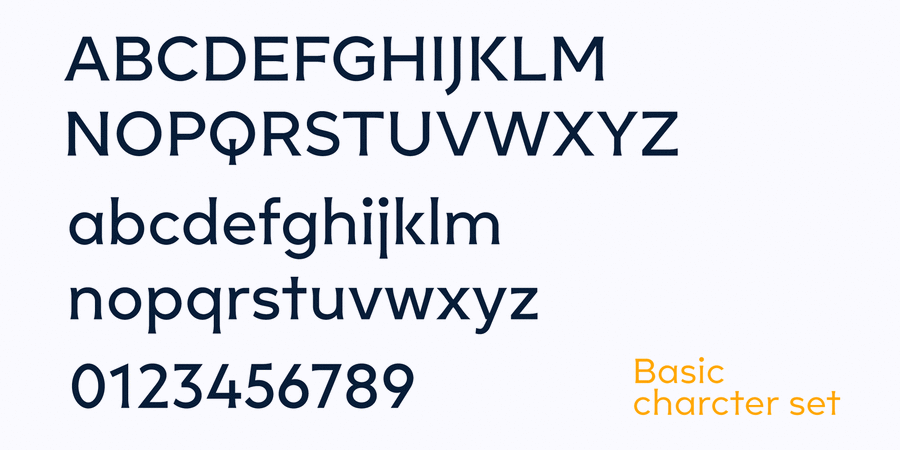
Zerno (18 шрифтів)
Zerno – гліптальний шрифт із геометричним корінням. Його симетричні делікатні засічки нагадують техніку різьблення по каменю. Завдяки насиченості від тонкого до наджирного, гарнітура досить універсальна, щоб її можна було використовувати в будь-якому середовищі – від екрану до рубленого граніту, від плакатів до акцентованого тексту. Шрифт розробив Олег Ліщук у 2021 році.
Особливості сімейства шрифтів ZernoХіт десятиліття:
Асоціації з сімейством шрифтів ZernoОсобистість і характер гарнітури:
тонкий, худий, витончений, холодний, делікатний, легкий, свіжий, модний, якісний, культурний, добірний, благородний, гармонійний, елітний, дорогий, красивий, майстерний, знаменитий, оригінальний, багатий, міський, прозорий, гострий, точний, статичний, чіткий, західний, рівний, розкішний, елегантний, ювелірний, естетичний, дорогоцінний, гламурний, сексуальний, ефектний, виразний, характерний, прекрасний, аристократичний, історичний, пафосний, унікальний, імперський, стійкий, переконливий, серйозний, значний, обов'язковий, солідний, стабільний, добротний, цінний, самостійний, відповідальний, твердий, надійний, яскравий, артистичний, кам'яний, різкий, сильний, героїчний, легендарний, мотивуючий, помітний, фундаментальний, урочистий, епічний, амбітний, авторитетний, римський, владний, видовищний, грандіозний, великий, величний, монументальний, впевнений, архітектурний, кінематографічний, християнський, традиційний, офіційний, важкий, квадратний, блатний, залізний, сталевий, колючий
парфумерія, дієта, туалетна вода, срібло, АСМР, краса, мода, ювелір, музика, ресторан, розкіш, гламур, Інстаграм, люкс, прикраса, дизайн, годинник, бутік, парфуми, преміум, готель, шоколад, коштовності, сервіровка, золото, музей, меморіал, пам'ятник, надгробок, скульптура, історія, меч, карти, мистецтво, архітектура, алкоголь, банкнота, монета, гроші, банк, акція, цінні папери, облігація, тютюн, віскі, фінанси, ломбард, антикваріат, гра, сигари, Барбершоп, Трофей, нагорода, кава, правосуддя, влада, суд, імператор, архітектор, обід, вечеря, кіно, сир, легенда, комп'ютерна гра, Біблія, взуття, бар, юрист, адвокат, нотаріус, сейф, м'ясо, казино, залізниця, паровоз, чіпси, спеції Гарнітура має ознаки стилів: